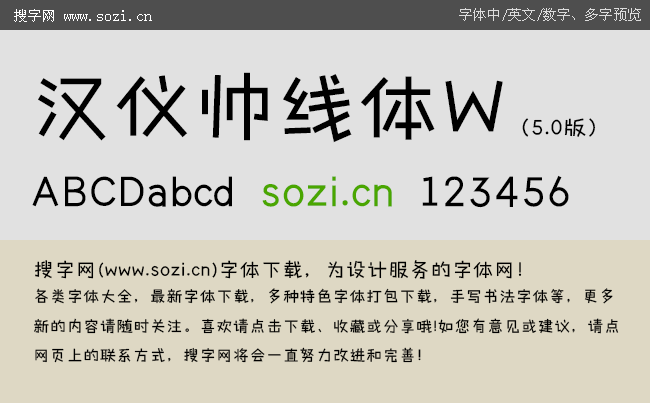
漢儀帥線體W5.0版
漢儀帥線體W5.0版是搜字網(wǎng)給大家提供一款漢儀字體公司出品的卡通中文字體下載,這款字運(yùn)用平頭和直線描繪,筆畫設(shè)計(jì)上硬朗,部件設(shè)計(jì)上有棱角、直接。力求現(xiàn)男孩子直率的性格。字與字之間依據(jù)字本身結(jié)構(gòu)特質(zhì)有大小變化,營(yíng)造跳躍和俏皮之感,使整體形象不呆板。相信你一定會(huì)喜歡在自己作品中用到這款中文字體!歡迎下載!